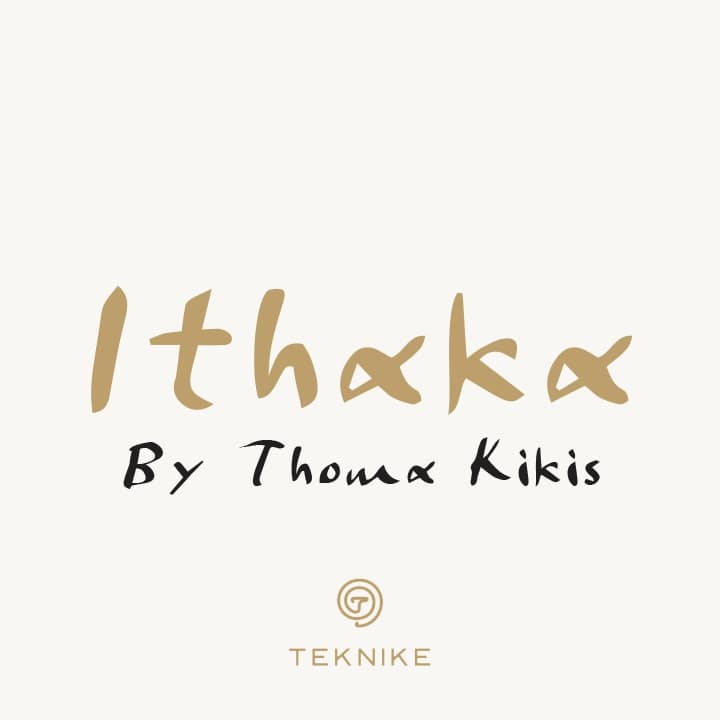
это выразительная антиква с характерными элементами рукописного стиля, созданная дизайнером Nat Watkins. Впервые появившись в 2019 году (по данным некоторых источников), он представляет собой гибрид классической засечки и игривой каллиграфии, что делает его уникальным инструментом для творческих задач. Шрифт отлично адаптирован для кириллического набора, сохраняя читаемость и эстетику в русскоязычных текстах. Его можно **скачать бесплатно** для личных проектов, чтобы добавить в дизайн теплоту и индивидуальность